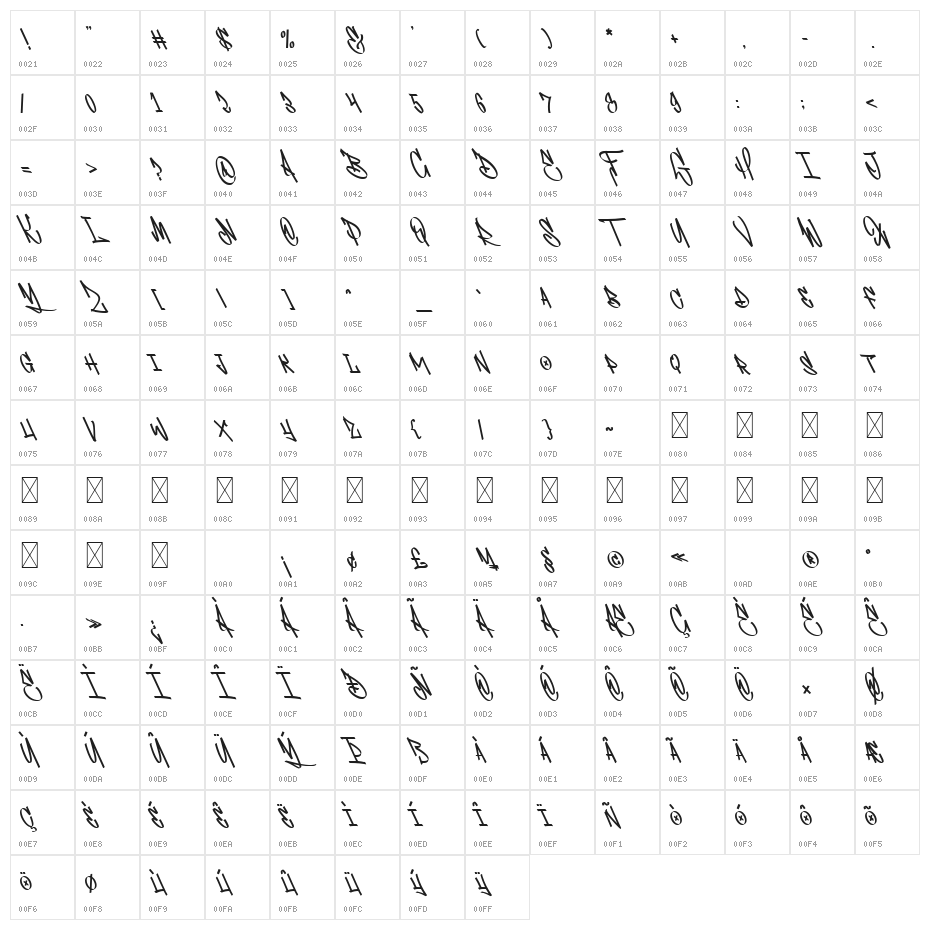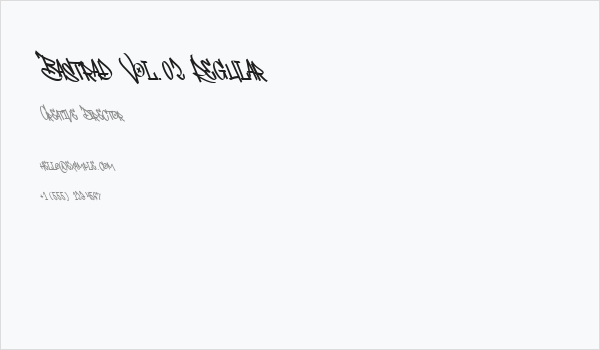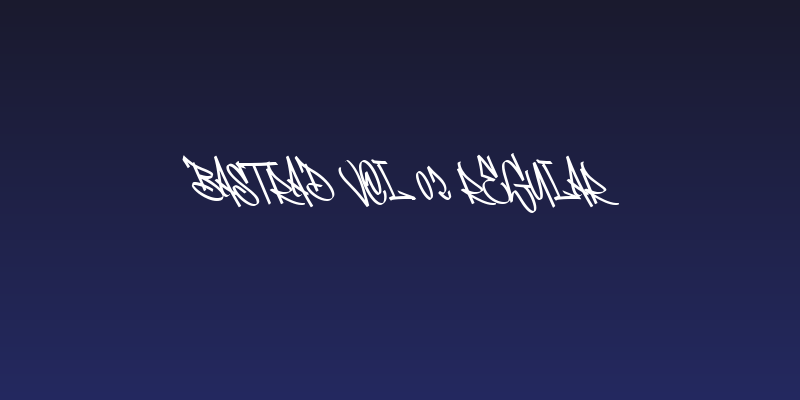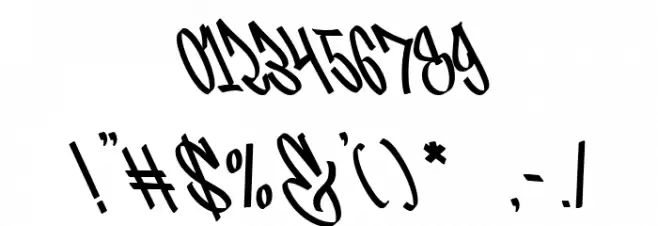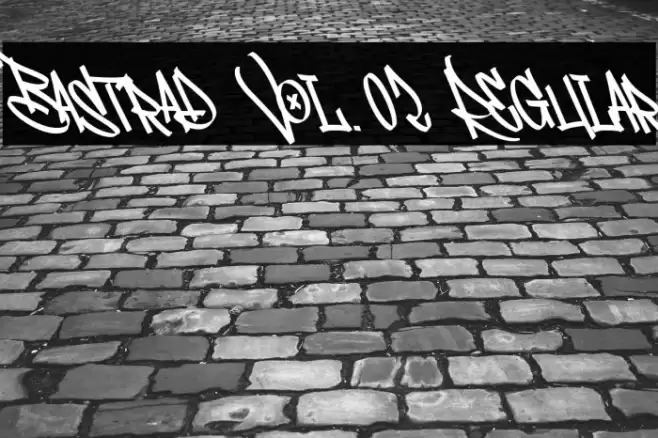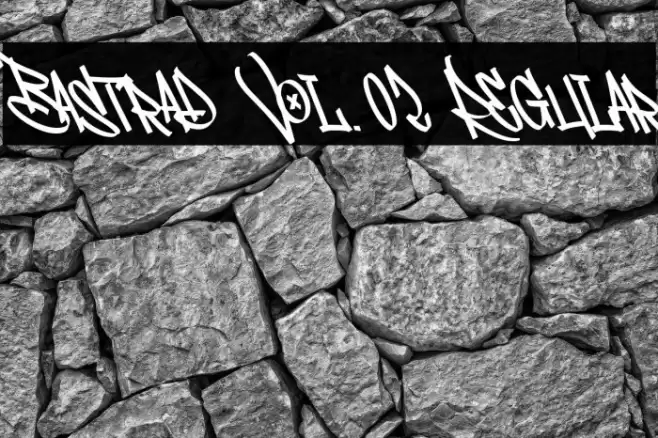
Bastrad Vol.02 Regular Font
Fonts by Ronny Studio
| Anwendungsfall | Logos, Headlines, Posters |
| Vorgeschlagene Projekte | Ideal for street art designs, urban-themed posters, music album covers, and edgy branding projects. |